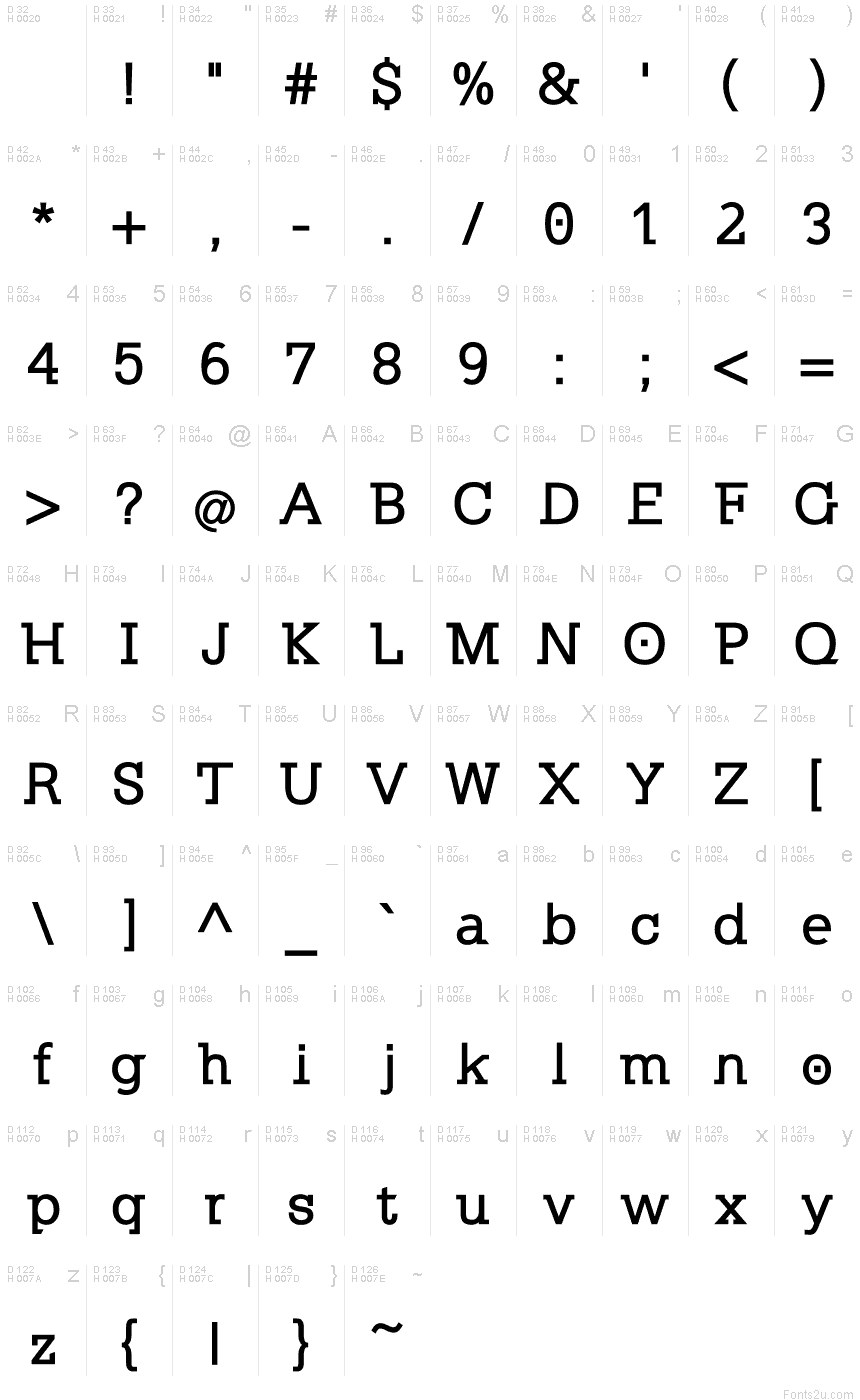
KleinSlabserif-Bold
Klein Slabserif Bold autorstwa Manfreda Kleina to darmowy krój pisma typu slab serif o wyrazistym, architektonicznym charakterze. Grube, kwadratowe szeryfy i solidny rytm nadają mu ciężar tradycyjnych czcionek drewnianych, a nieoczekiwane cięcie w literze „K” oraz czyste, otwarte światła wewnątrz znaków sprawiają, że całość prezentuje się ostro i nowocześnie, unikając efektu retro. W rezultacie otrzymujemy odważny, wyrazisty krój, który przywodzi na myśl druk czarną farbą na papierze i od pierwszego wejrzenia budzi poczucie pewności i zdecydowania.
Używając Klein Slabserif Bold, nagłówki i logotypy natychmiast przyciągają uwagę, nie sprawiając wrażenia krzykliwych czy udziwnionych. Ten darmowy font świetnie sprawdza się na plakatach, okładkach książek, w redakcyjnych tytułach, na opakowaniach czy w wyrazistych banerach internetowych, które potrzebują mocnego typograficznego zakotwiczenia. Sprawdzi się także w oznakowaniu czy grafikach eventowych, gdzie liczy się czytelność z odległości. Zestaw go z lekkim, geometrycznym krojem bezszeryfowym w tekście głównym i pozwól, by Klein Slabserif Bold przejęła główną rolę w momentach, które wymagają zdecydowanego wyrazu.